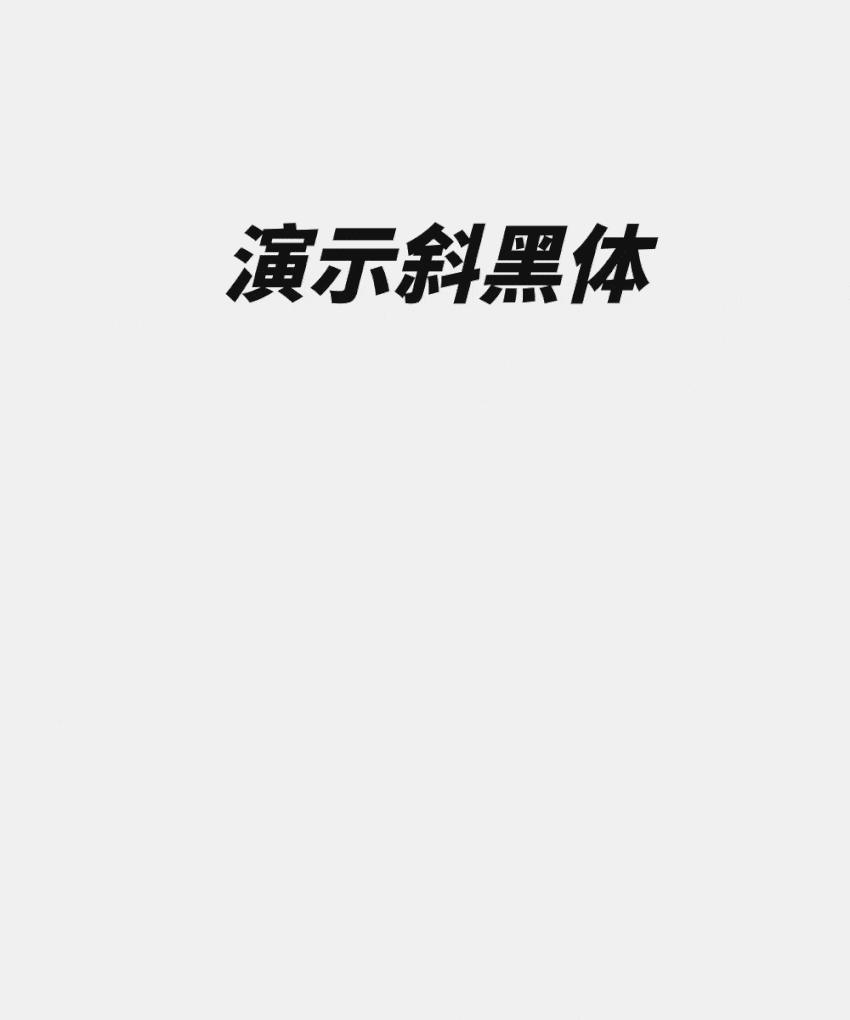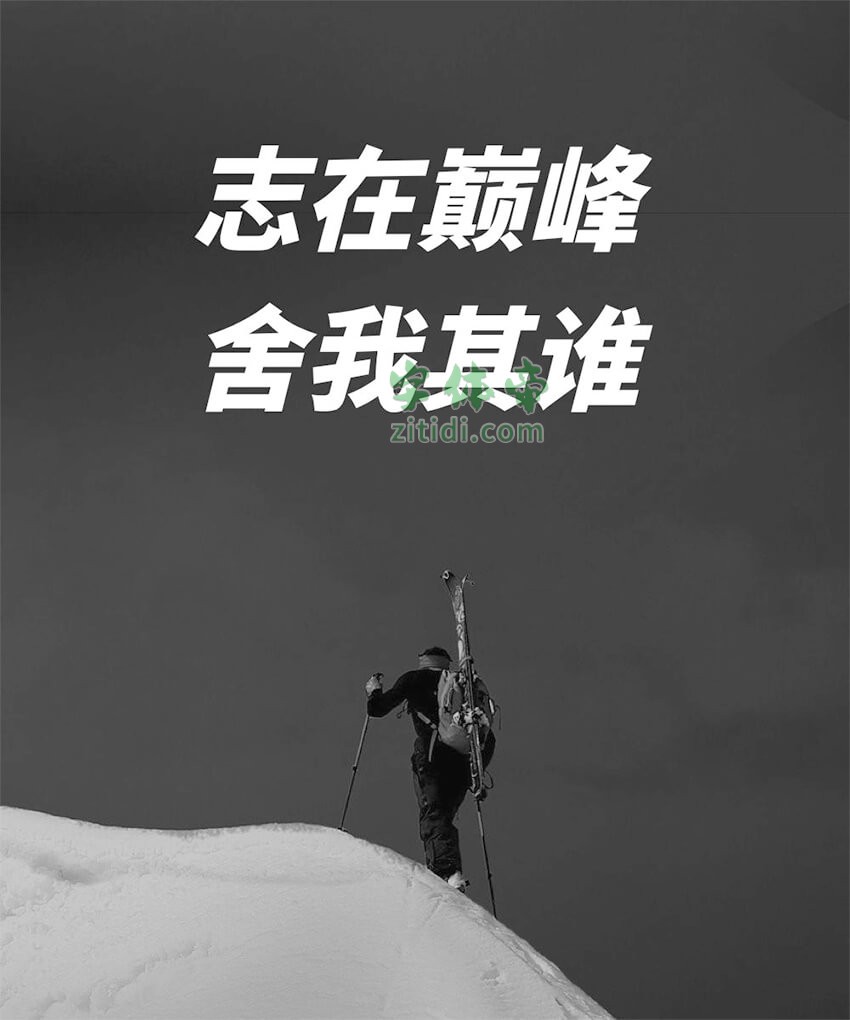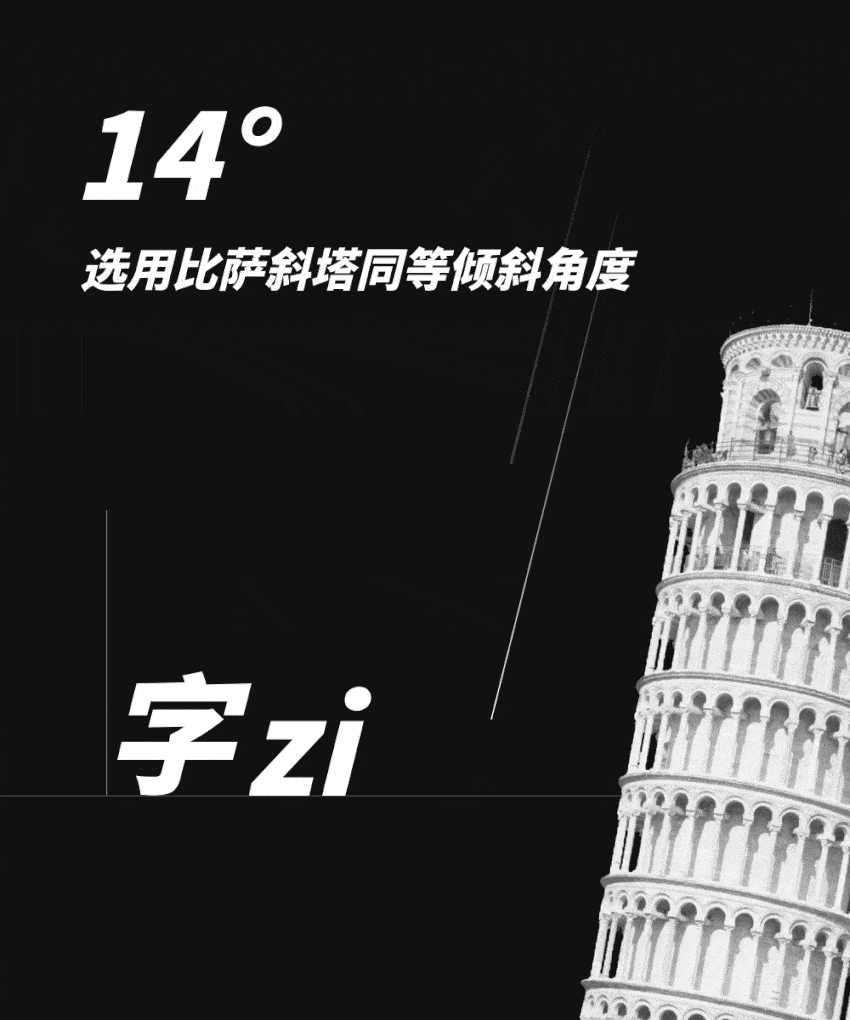
执念的设计者为了追求这种即视感,必然会选用倾斜体文字,通识性的做法是在AI或Sketch中打出中文,然后做角度转换,再复制回Keynote中,对于需要制作多页幻灯片的人来说,这无疑是一种负担。
在PPT中一键倾斜就可以完成的事情,在Keynote中往往变得很复杂,很多人在更换了MAC电脑以后,依旧抛弃Keynote而使用 PPT 的原因大概是来自这三点:
- Keynote并不支持字体渐变与矢量化处理
- 线条和边框不能设置渐变色
- Keynote不支持中文倾斜字
当然,上面的两点其实已经解决了,具体你可以参考文章:神破解Keynote艺术字与线条
所以,这一次主要是解决第三点问题:Keynote如何使用倾斜字?
甚至连你们的网黄Simon阿文都在抱怨Keynote:
所以人生哥亲自动手,改造出一款 Keynote 可用的倾斜字,同样也可以简化 PPT 中的操作步骤,于是便有了这款字体:演示斜黑体。
“演示斜黑体”是一款书写很新颖的字体,字体大方,适合各种设计作品使用!欢迎下载!